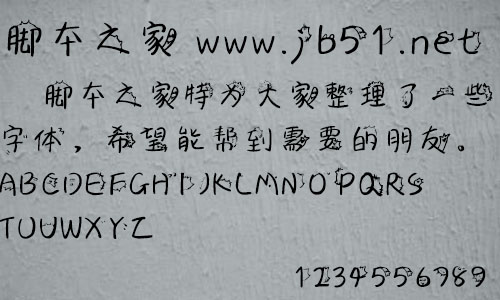
Aa喵大仙一款不錯的的藝術(shù)字體,由Aa字庫出品,字體筆觸適中,點(diǎn)綴了一些卡通元素進(jìn)行裝飾,具有很好的視覺感,適合應(yīng)用于藝術(shù)設(shè)計(jì)、平面宣傳設(shè)計(jì)、網(wǎng)頁設(shè)計(jì),書法字帖等領(lǐng)域,需要的朋友可以前來本站下載。